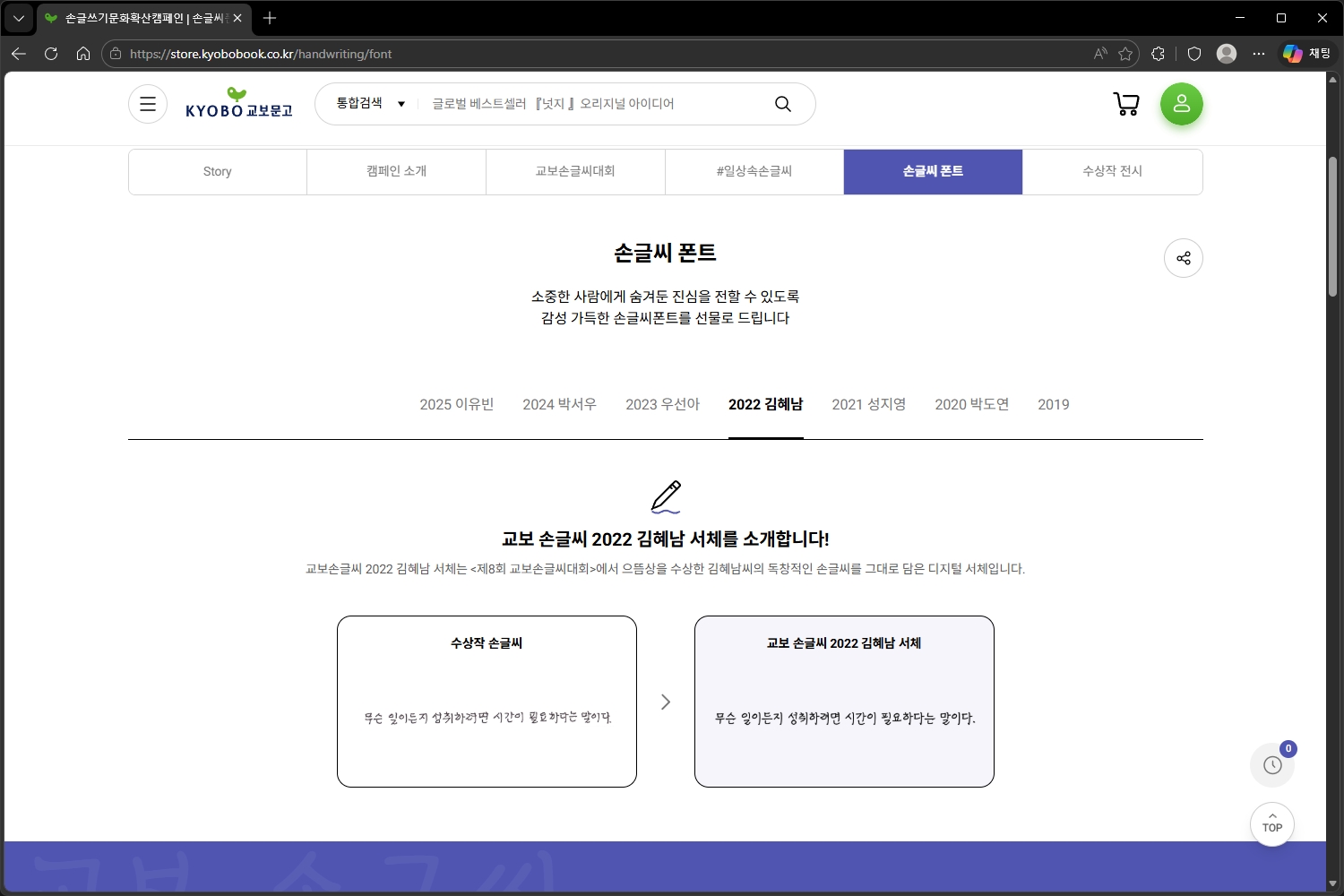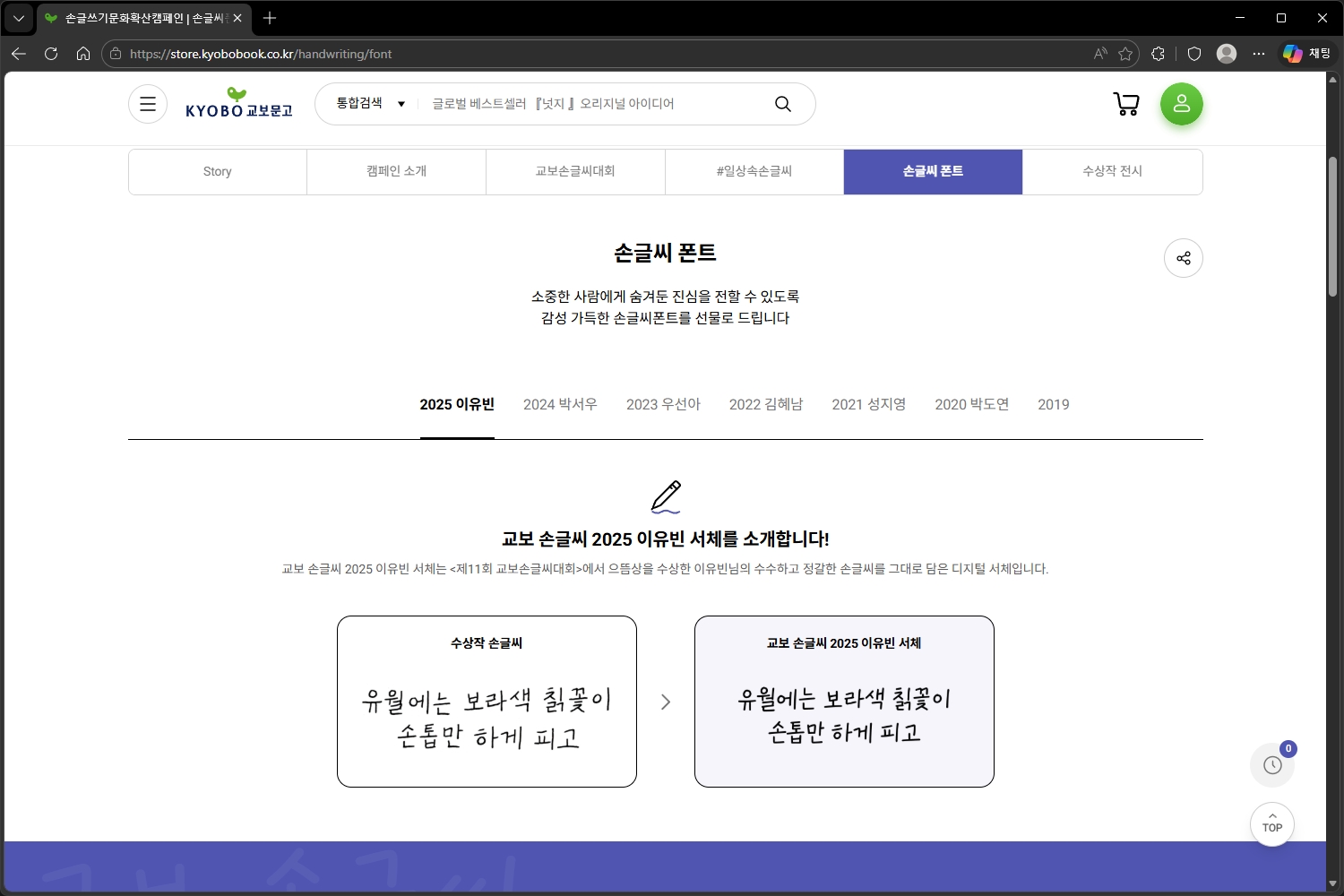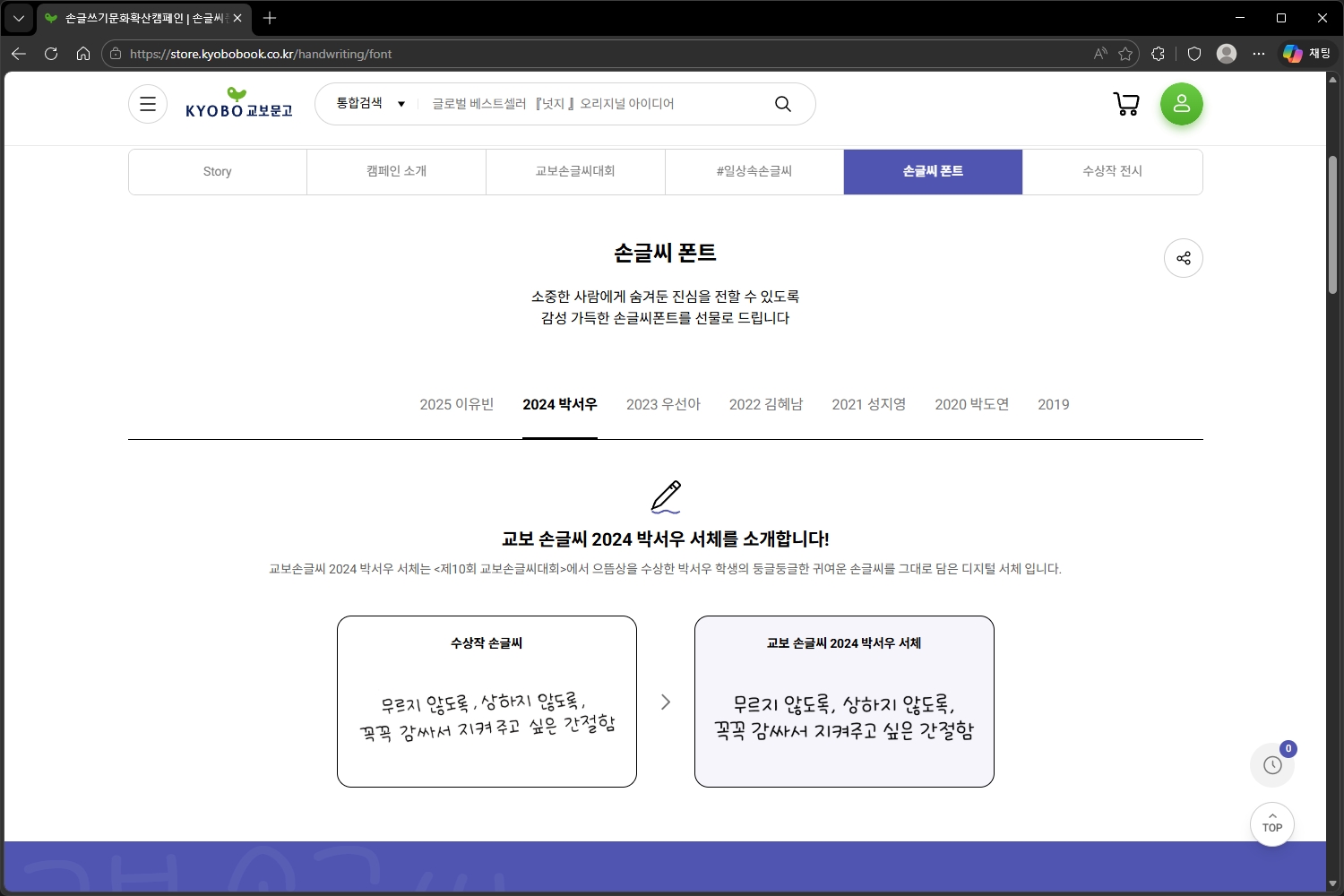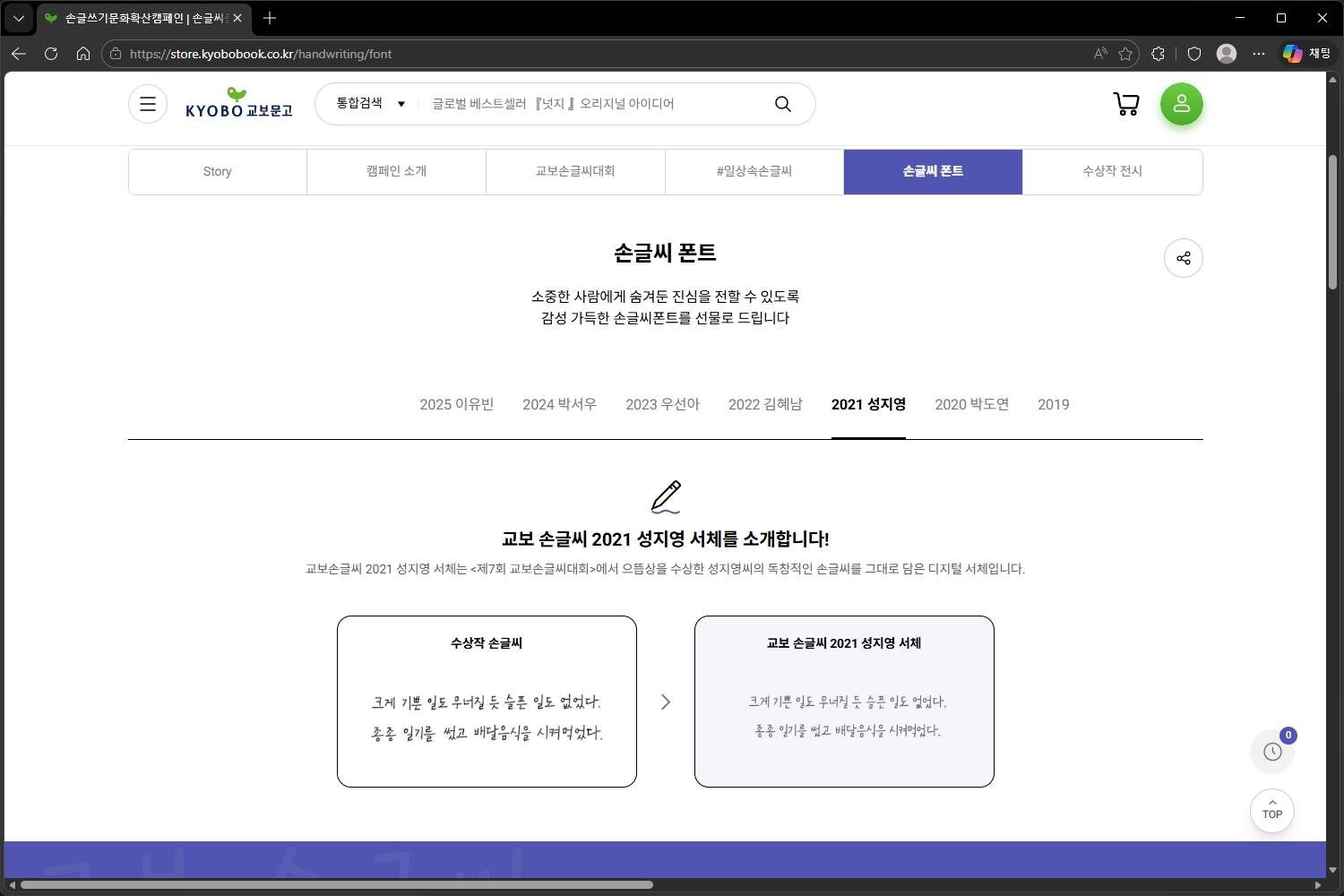
교보문고 손글씨 폰트
브이로그나 숏폼 등 다양한 목적의 영상을 제작하다 보면 가장 신경 쓰이는 부분이 바로 폰트라고 할 수 있는데요. 분위기에 맞는 서체를 찾기가 생각보다 어렵고 여기에 저작권 관련 이슈까지 더해지면 더욱 머리가 아파지게 됩니다.
그래서 이번 포스팅에서는 상업적으로도 사용할 수 있는 무료 폰트 교보문고 손글씨에 대해서 자세하게 살펴보도록 하겠습니다. 참고로 연도별로 준비되어 있어서 자신의 취향이나 영상의 분위기에 맞는 서체를 선택할 수 있습니다.
교보 손글씨 대회
교보문고에서는 매년 손글씨 대회를 진행하고 있는데요. 1등을 선정해서 디지털 서체로 제작하고 있습니다. 일종의 사회공헌적인 목적이 큰 행사라고 생각되었습니다. 그리고 선정되신 분들에게도 평생 추억으로 남을 것 같습니다.
2025년 이유빈
2024년 박서우
2023년 우선아
2022년 김혜남
2021년 성지영
교보문고 손글씨 폰트는 2019년부터 2025년까지 총 7개로 구성되어 있는데요. 가장 최신 버전은 2025년 이유빈님이고 2019년은 아마 12살 어린이의 폰트라서 이름이 없는 것으로 보입니다. 각각의 서체들은 개성이 뚜렷한 편입니다. 일부로 매년 다른 느낌의 서체를 선택한 것처럼 보이는데요. 취향에 따라서 다운로드 받아서 사용할 수 있습니다.
교보 손글씨 폰트
교보문고 손글씨는 고딕과 궁서체와는 다르게 약간 자연스러운 느낌을 주는 편입니다. 그래서 딱딱한 형태의 영상보다는 브이로그와 같은 영상에 사용하기에 적합한 폰트라고 생각되었습니다. 그래서 영상 제작에 필요한 폰트가 고민이신 분들은 교보문고 손글씨를 한 번 고려해 보시길 바랍니다.